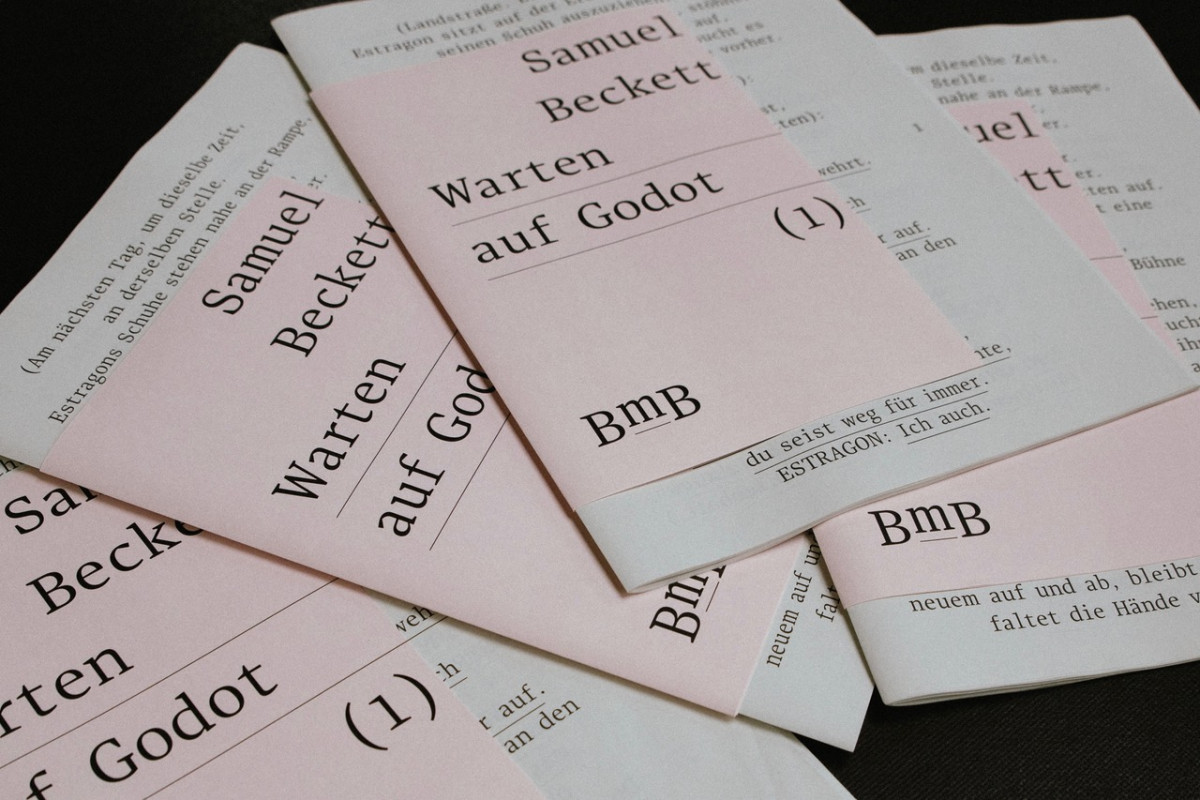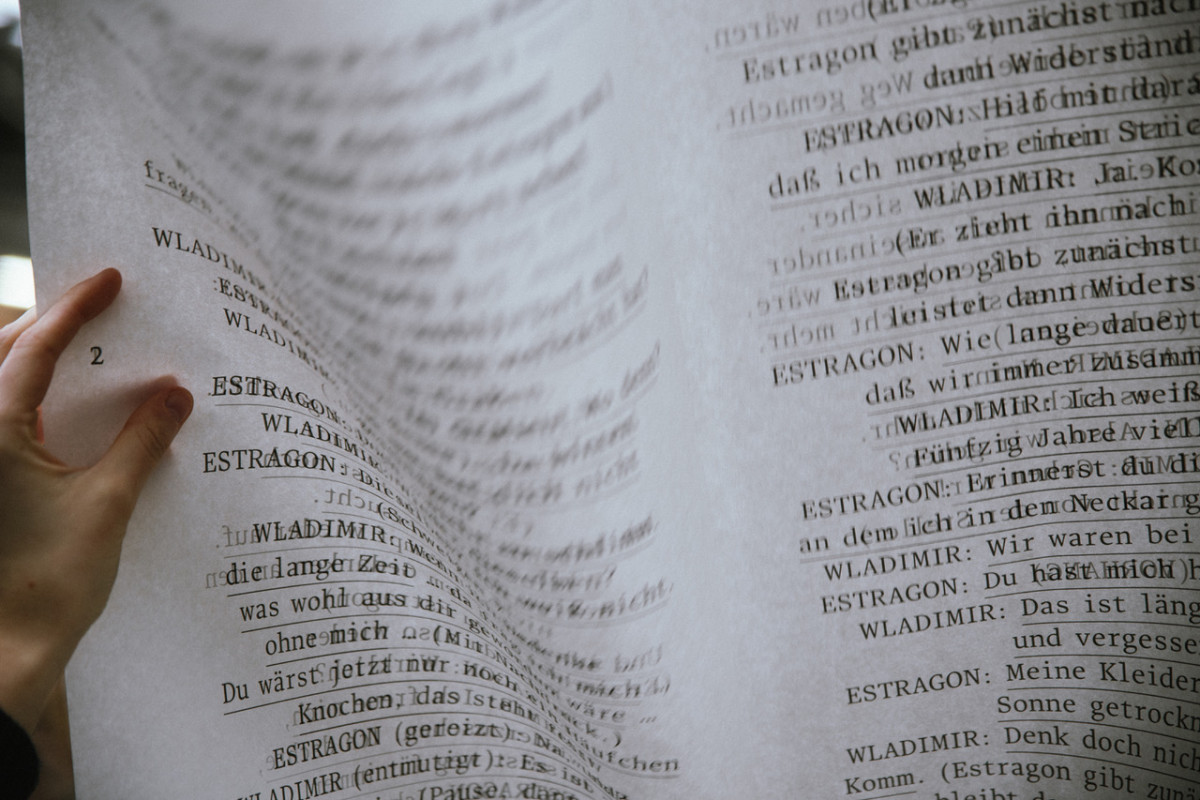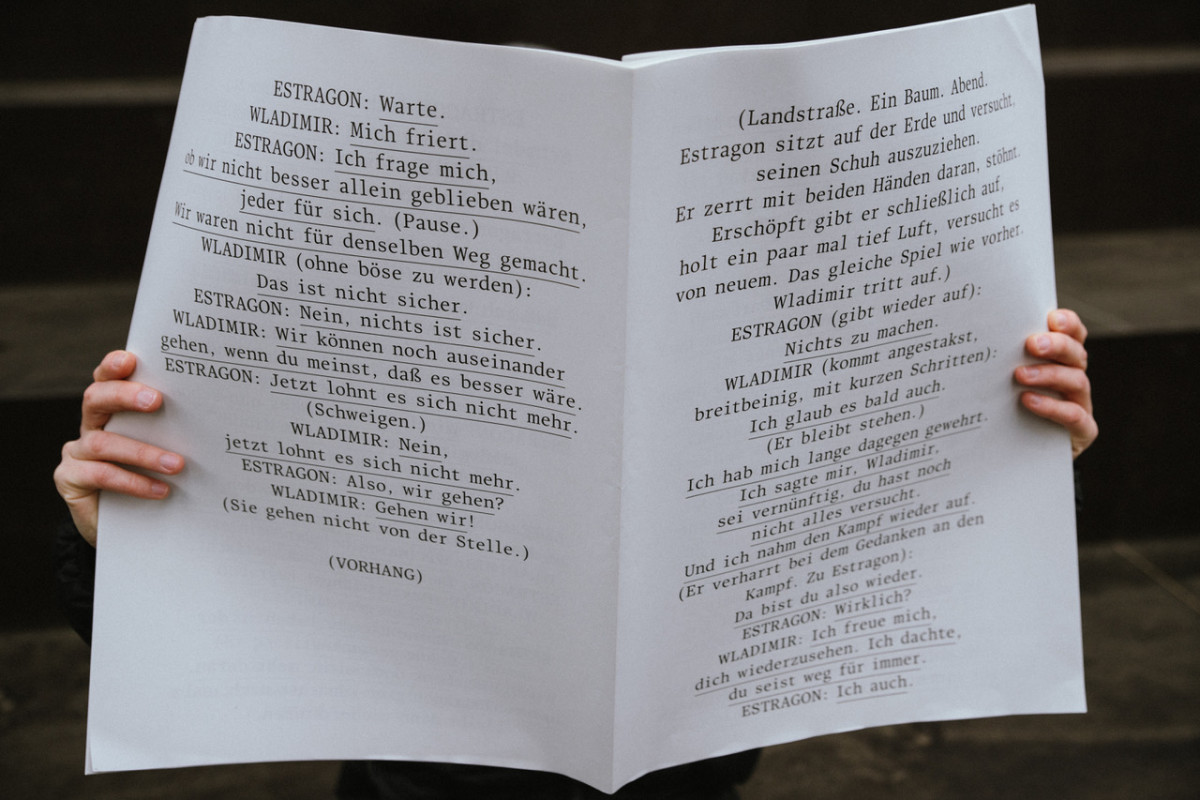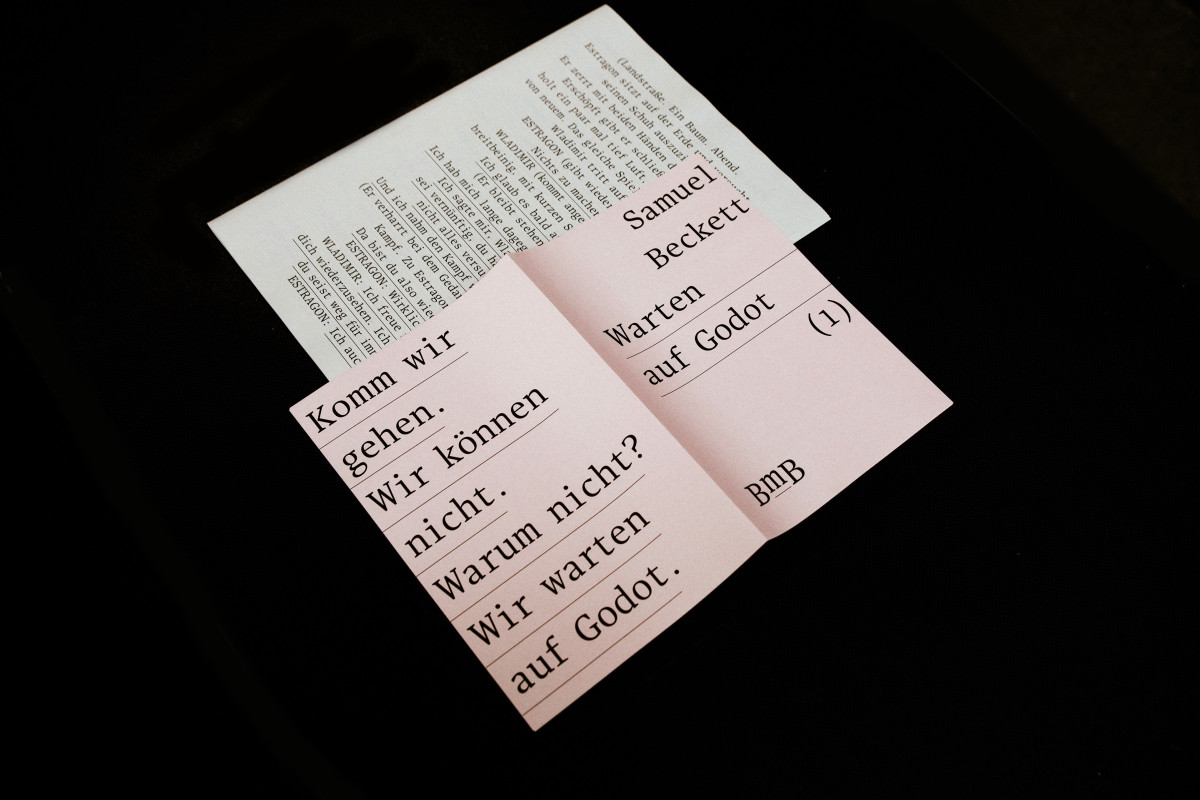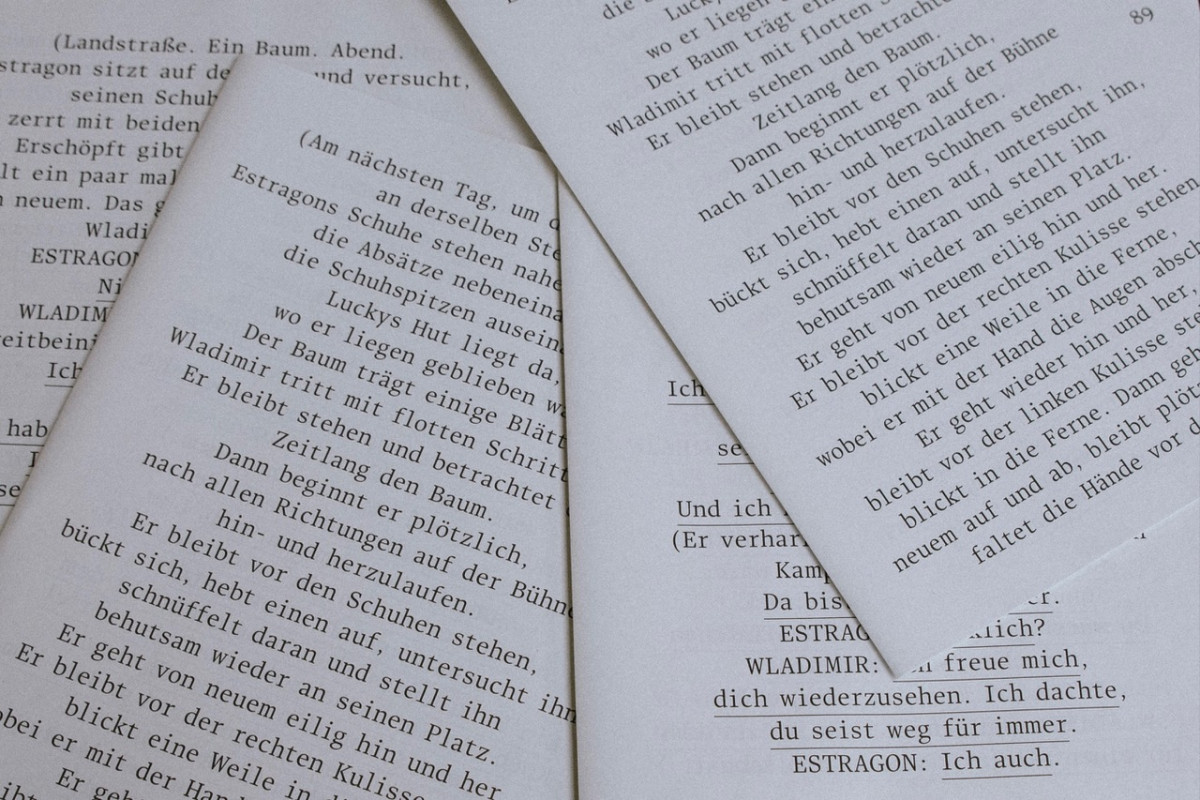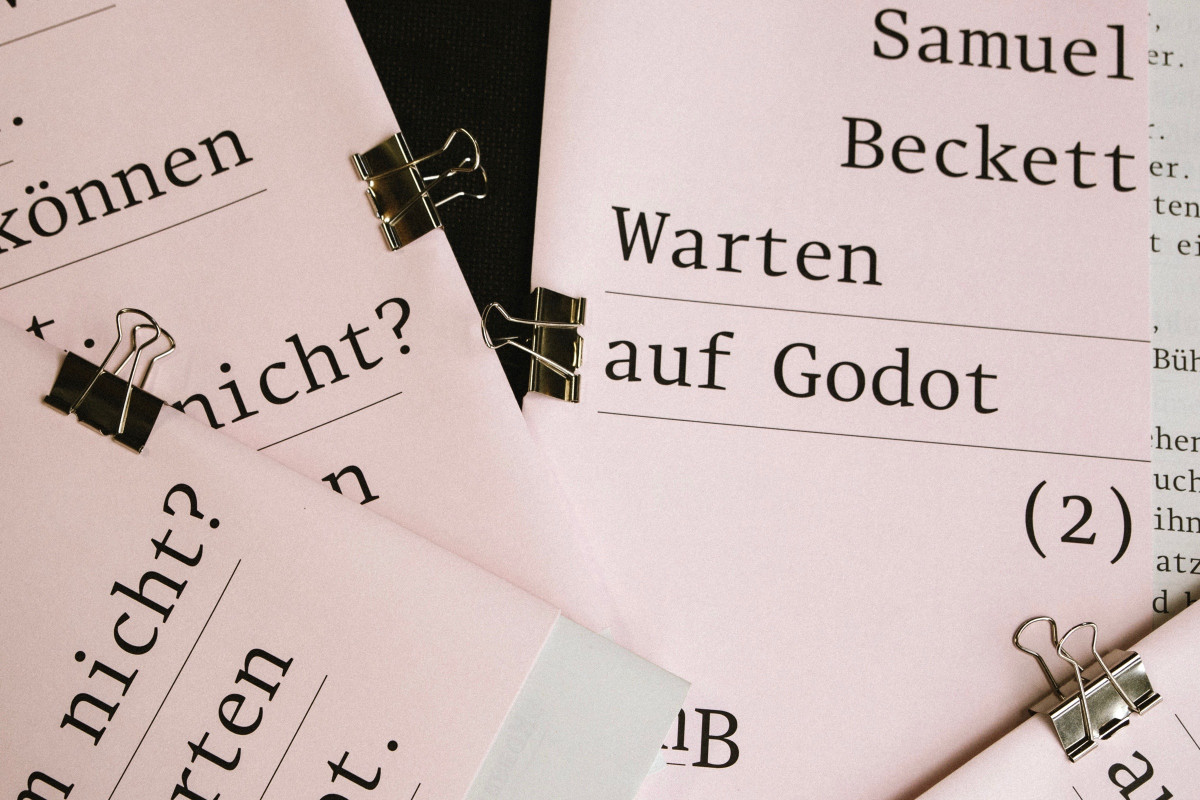
Die experimentelle Buchgestaltung von Samuel Becketts "Warten auf Godot" untersucht das Warten als existenziellen Zustand. Das Aushalten von Leere und Bedeutungslosigkeit steht im Fokus – vermittelt durch absurde, minimalistische und humorvolle Mittel.
Das große, ungebundene Format mit losen ineinandergelegten Bögen erzeugt ein Gefühl von Fragilität und Unentschlossenheit. Zusammengehalten wird es nur durch die Leser*innen selbst – wie auch Wladimir und Estragon nur durch die Abwesenheit Godots verbunden sind.
Typografisch wird auf eine feste Ordnung verzichtet. Der Text richtet sich mittig aus und findet so seine eigene Form. Gesprochenes wird unterstrichen und Regieanweisungen stehen in Klammern.
Die Kombination aus großem Format und dünnem Papier erschwert das Lesen bewusst und macht Stück zu einer aktiven, absurden Erfahrung.
The experimental book design of Samuel Beckett's “Waiting for Godot” examines waiting as an existential state. The focus is on enduring emptiness and meaninglessness - conveyed through absurd, minimalist and humorous means.
The large, unbound format with loosely interlaced arcs creates a feeling of fragility and indecision. It is only held together by the readers themselves - just as Vladimir and Estragon are only connected by the absence of Godot.
Typographically, there is no fixed order. The text is centered and thus finds its own form. Spoken words are underlined and stage directions are in brackets. The combination of large format and thin paper deliberately makes reading difficult and turns the play into an active, absurd experience.